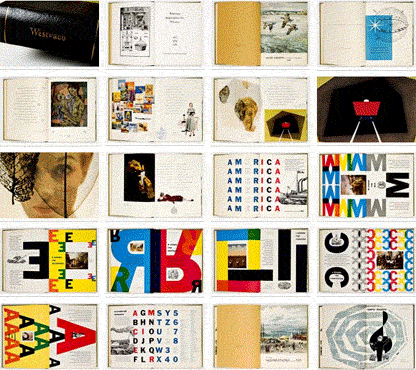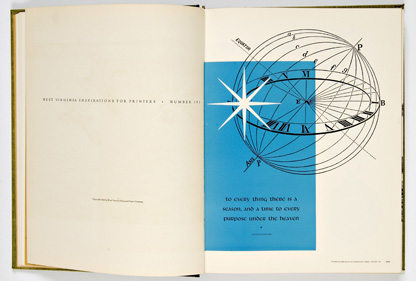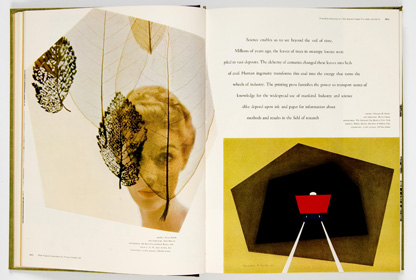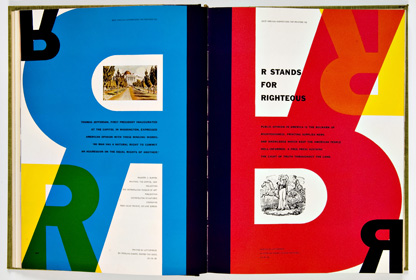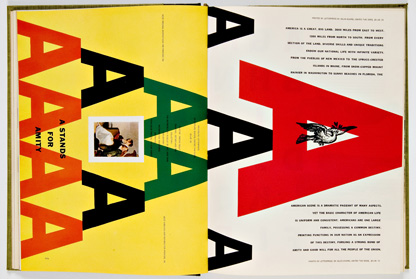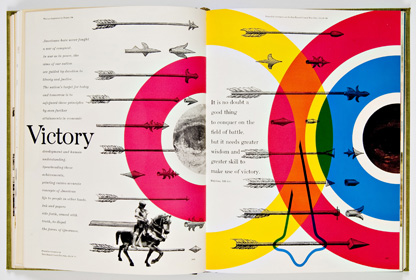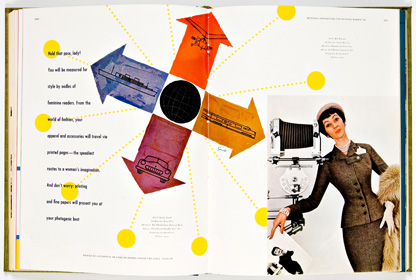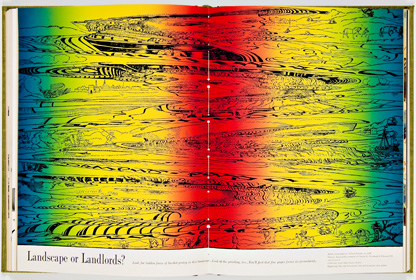
Westvaco II | la période 1953 à 1955 | la machine à remonter le temps (reloaded)
Dans un article en date du 10 mai 2006, Design & Typo avait publié l’album de graphic trends du fabricant de papier Westvaco (1956-1961), nous vous présentons aujourd’hui le cahier de tendances précédent, celui consacré aux années 1953, 1954, 1955. On y retrouve bien sûr les célèbres recherches-lab de Bradbury Thompson mais aussi le travail de Ben Collins. Ce dernier, fait une œuvre d’une facture beaucoup plus classique. Typographies soignées, personnages et objets détourées, blancs tournants majestueux, interlignes blanchis. Très peu de superpositions, mais tout de même… Et bien entendu par comparaison on devine les risques que Bradbury va prendre en rompant avec les codes classiques pour aborder courageusement l’ère post-gutenbergienne. A New-York Andy Wharol crée La Factory et use de même dans nombre de ses créations des couleurs primaires superposées. Thème récurent chez B.Thompson mais qui trouve là une légitimité industrielle puisque les primaires s’adressent aux imprimeurs, destinataires de ces cahiers de tendances Westvaco. Quoiqu’il en soit, en examinant ces cahiers on peut constater encore cette modernité absolue qui nous vient de la jonction entre typographie suisse et handlettering américain. La IIe guerre mondiale vient à peine de s’achever. C’était il y a huit ans, moins d’une décennie, et les graphistes designers sont encore tout prudents, voire même un peu lourds, sauf Bradbury qui entrevoit déjà un style et une intervention efficace, hors du temps. Cela dit, pour nous, spectateurs de 2007, quelque cinquante ans ont à peine passé et nous découvrons à travers cette machine à remonter le temps, que justement ce temps n’est pas si loin, par la maîtrise des codes de mises en page, du rythme et de la musicalité de ces pages… c’est très rock n’roll.
design et typographie : Ben Collins
artist: Ernst Beadle, art director: Paul Darrow, quadrichromie trame 120
Bradbury Thompson | imprimé sur papier couché deux faces, quadri, trame 133
Bradbury Thompson pour le graphisme.
Artist: Hans Erni, Art Director: Paul Smith & Marce Mayhew, photogravure demi-teinte (par opposition au trait) en trame 110
Artist: George Giusti, Art Director: King Rich, quadri, trame 120
Artist: Erhard Schoen (gravure sur bois 1534), impression quadri en mélange des couleurs directs à l’encrier
1954, un cours de photogravure pour les art directors